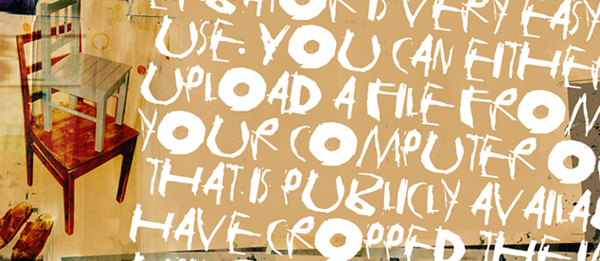
يُعد Tasapainoaisti من Junkohanhero خط عرض مجاني بأسلوب «trash» (خشن) يعطي انطباعًا أوليًا بأنه مقصوص يدويًا. تبدو الحروف وكأنها نُحتت بضربات خشنة، مع حواف ممزقة، وزوايا حادة، وصورة ظلية متوترة؛ مما يجعله أقرب إلى تصاميم منشورات البانك والمجلات المستقلة (Zines) منها إلى ستايل الجرونج المصقول.
يعمل الخط بشكل رائع في عناوين الملصقات، وأغلفة الألبومات، وتصاميم التزلج، وعناوين أفلام الرعب، وبطاقات العناوين القصيرة حيث تحتاج إلى خط مجاني يبدو مخدوشًا وعاجلًا وذا طابع يدوي. وبما أن أشكاله تظل جريئة وغير منتظمة في الوقت نفسه، فهي مناسبة أيضًا للرموز (Monograms) أو الحروف الاستهلالية الكبيرة التي تتطلب لمسة عفوية وارتجالية بدلاً من الرموز الرسومية النظيفة.